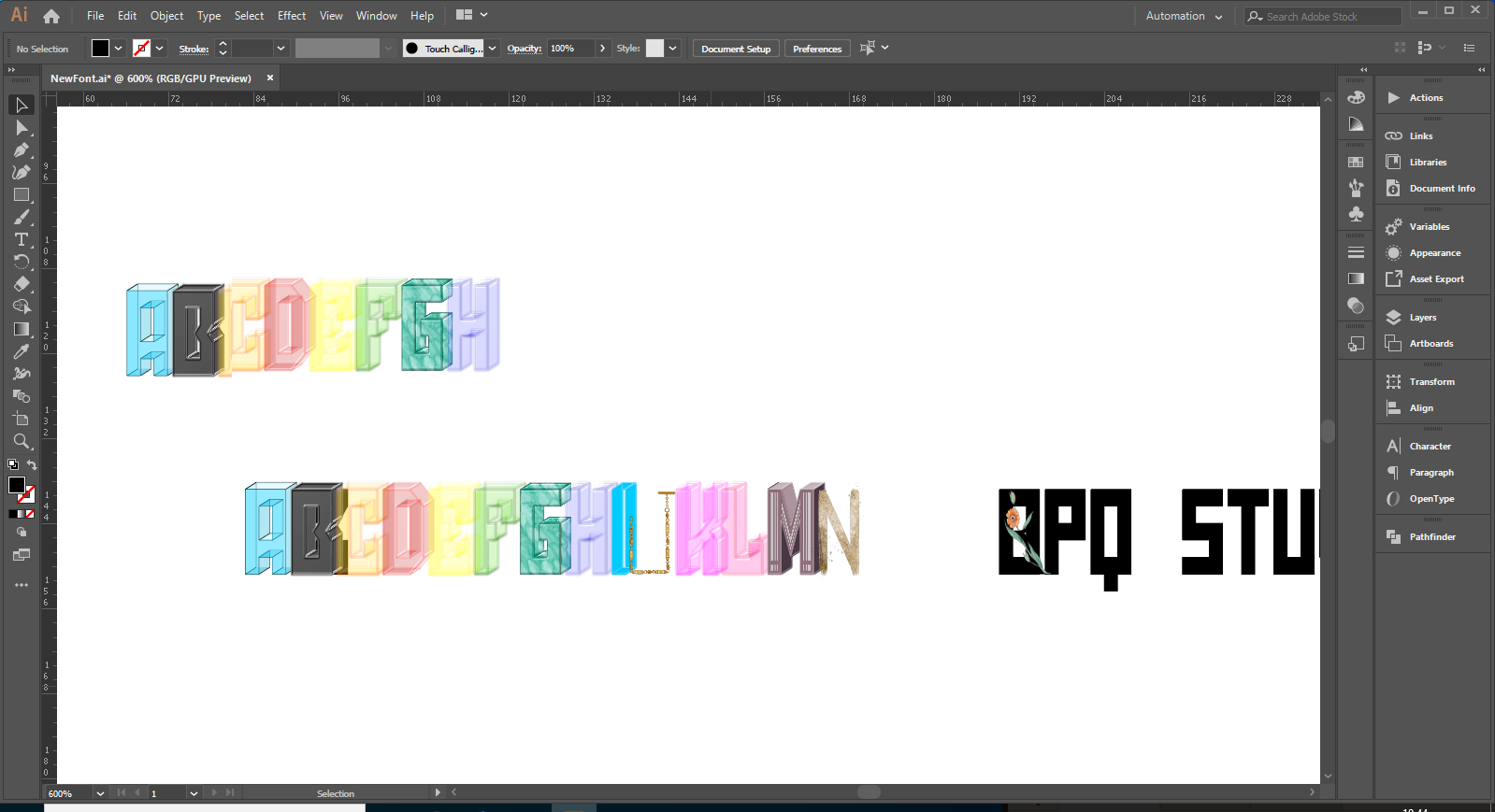
ฟอนต์สี มณีSVG
เพิ่งมีเหตุอยากจะใช้ color font เลยเข้ามาศึกษาดู พบว่าไปไกลมากแล้ว  ฟอนต์ตัวนี้ทำเป็นฟอนต์ทดลอง สีแบบโปร่งใส และซ้อนทับกัน
ดังนั้น ไม่เหมาะทั้ง display type และ text type :48:  อ้าว!แล้วทำมาทำไม.. :08: ก็ทดลองไง   :30:
color font ตัวนี้ ใช้เทคนิค OpenType SVG ดังนั้นจะแสดงผลได้แต่ s/w บางตัว เช่น adobe, firefox ส่วน Microsoft, chrome ไม่ work  ที่เหลือไม่ทราบ ฝากทดสอบและบอกผลด้วยเด้อ!!
กรณีที่ s/w ไม่สามารถแสดงผล color font ได้ จะแสดงเป็น font ปรกติ หน้าตาแบบนี้
ฺเล่าเรื่อง OpenType SVG ที่ได้ศึกษามาหน่อย  เผื่อมีคนมาแนะนำเพิ่มเติม
1. เริ่มจากการ download color font ที่มีแจก มาทดลอง  พบว่า  บางตัวแสดงสีได้เฉพาะ firefox แต่ chrome เป็นสีดำ
2. ส่วนอีกประเภท คือ color font ที่แสดงผลสีได้ทั้ง firefox และ chrome
3. เอา color font ของไทย มาทดสอบดู  พบว่า ฟอนต์รวมมิตรของ พจน เท่านั้นที่แสดงได้ทั้ง  firefox และ chrome  และแน่นอน แสดงสีได้บน MS word ด้วย.. ว๊าววว
3.1 จึงได้รบกวน พจน  ให้ตรวจ color font ต่างๆหน่อยว่ามันต่างกันยังไง
color font ที่ download มา
color font ของ พจน
3.2 ได้ข้อสรุปจาก พจน ว่า
3.2.1  color font แบบข้อ 1 ใช้เทคนิคที่เรียกว่า OpenType SVG  โดยการแยกสร้าง font และ svg ออกจากกัน
3.2.2  color font แบบข้อ 2 ใช้เทคนิคที่เรียกว่า COLR/CPAL  (ซึ่งใช้ใน color emoji font นั่นแหละ)
3.2.3  ส่วนของ พจน  มีทั้ง 2 เทคนิคเลยจ้า
4.1 ก็ search ไปเจอ tools ที่สร้าง OpenType SVG font ได้  เลยเอามาทดลองทำ color font  โดยปรับฟอนต์เดิมที่มี ซึ่งบังเอิญใช้ inkscape ซึ่ง support SVG อยู่แล้ว พบว่า
4.1 เอารูป SVG มาใช้ได้เลย  โดย color font จะจัดการเรื่อง font ตามที่กำหนดไว้ใน font ปรกติ  และแสดงผลโดยใช้ภาพจาก SVG
4.2 สามารถใส่ effect ของ SVG ได้เลย แต่การแสดงผล ขึ้นกับ tools แต่ละตัวเลย  อาจจะไม่เหมือนต้นฉบับที่สร้างด้วยซ้ำ
4.3 สามารถแสดงผลแบบ bitmap คือเอารูป PNG มา save เป็น SVG แล้วใช้ได้ด้วย  ดังนั้นก็แสดงเป็นรูปเนียนๆได้เลย
4.4 SVG font จะมีขนาดใหญ่บึ้ม ตาม effect ที่เราใส่ลงไป ส่งผลให้เครื่องอืดทีเดียว ไม่ใช้ slim อย่าง concept ฟอนต์แบบสมัยก่อน  ยิ่งเอารูปมาแสดงผลเนียนๆแล้วไม่ต้องพูดถึง hang ได้เลย แต่ผลงานที่ไป search ดูๆมาก็ เนียนสวยมาก ราคาสูงดีด้วย
inkscape ก่อนสร้างฟอนต์ SVG
แสดงผลใน firefox
ใน AI by พจน
ใน FontCreator by พจน
ใน MS word by พจน
เพิ่มเติม SVG สามารถ animate ได้ด้วย ดังนั้น color font ประเภทนี้ ก็สามารถเคลื่อนไหวได้ด้วยนะ (ไปกันใหญ่แล้ววววว)
หมายเหตุ แต่เนื่องการใส่ effect มันทำให้ ฟอนต์ ขนาดโตมากไป SOVc_maneeSVG ก็เลยทำแค่เป็นฟอนต์สี 3D โปร่งแสง เท่านั้น
แบบนี้เหมือนเอา SVG มาวางเรียงกันเลยใช่ไหมครับ
มีไอเดียว่าอยากทำ Animation Font
.svg มันทำ animation ได้ คิดว่ามันสามารถทำ animation ฟอนต์ได้ตามวิธีนี้
แต่ลองดูแล้วก็ยังไม่เวิร์คเท่าไหร่
นอกจากนี้มี color variable font ด้วยนะครับ https://www.harbortype.com/fonts/rocher-color/
ตอนเห็น นึกถึง Jipatype เลย  แต่ก็ยังตันกับความ variable font อยู่ 55
ใช่ครับ ฟอนต์ กับ SVG เป็นคนละ layer กัน  เป็นอิสระต่อกันเลยครับ  เพียงแต่ ขนาด SVG ต้องไม่กว้างใหญ่กว่า ขนาดฟอนต์แต่ละตัวที่กำหนดไว้ครับ
รูปนี้อธิบายได้เห็นภาพ ว่า color font 2 แบบนี้ จัดการแตกต่างกันอย่างไร